Top 7 font chữ in hoa đẹp cho dân thiết kế
Font chữ in hoa đẹp Lato
Lato (có nghĩa là mùa hè trong tiếng Ba Lan) là một họ của phông chữ sans-serif được thiết kế bởi Łukasz Dziedzic vào mùa hè năm 2010 và sau đó được Google phát hành theo Giấy Phép Phông Chữ Mở (OFL). Phông chữ Lato nổi bật với những đường nét bo tròn nhẹ nhàng mang đến sự ấm áp của mùa hè, nhưng không làm mất đi sự sang trọng nhờ thiết kế cổ điển. Rất thích hợp cho những font chữ khi In tem nhãn bao bì cho các xưởng in.
Font TH Cemains Việt hóa
Font chữ hoa TH Cemains Việt hóa là kiểu chữ in hoa toàn bộ, mang phong cách kỹ thuật rõ ràng, cứng cáp và hiện đại, đã được bổ sung đầy đủ dấu tiếng Việt để sử dụng thuận tiện. Font có nét chữ gọn gàng, dễ đọc, đảm bảo tính chính xác khi trình bày thông tin, đặc biệt phù hợp cho khung tên bản vẽ, chú thích kỹ thuật, tiêu đề hồ sơ thiết kế và các ấn phẩm mang tính chuyên môn cao.
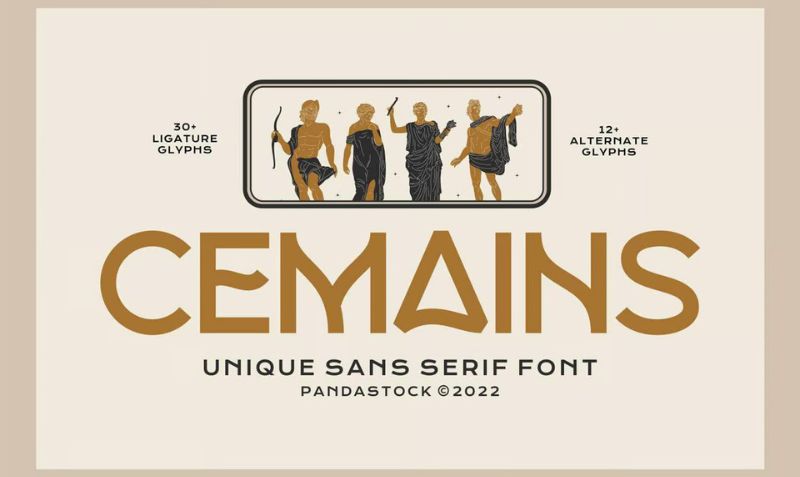
Font iCielBC Downtown
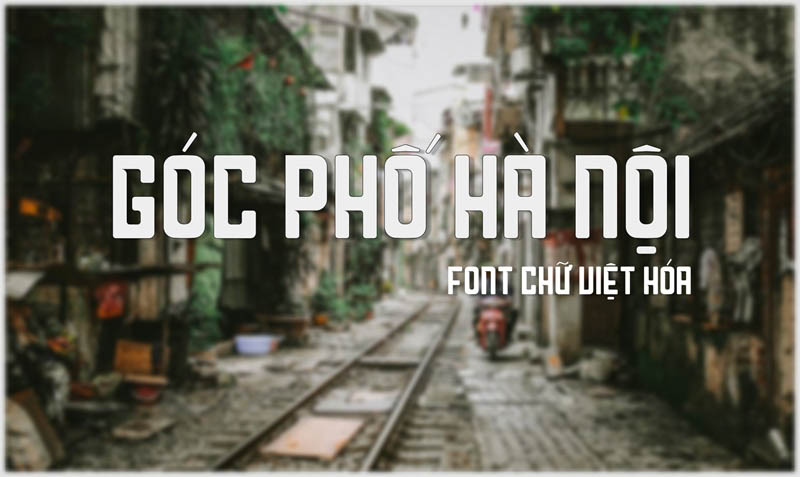
Được thiết kế bởi một bạn nữ ở Hà Nội, phông chữ iCielBC Downtown được lấy cảm hứng từ những tấm biển vẽ tay, những hình ảnh bình dị và màu sắc thời bao cấp. Tuy nhiên, chỉ nên sử dụng font này cho mục đích cá nhân, nếu dùng để thiết kế sẽ cần phải mua bản quyền.
Font SVN-Product Sans
Đây là phông chữ do Google Inc thiết kế với mục đích xây dựng thương hiệu riêng và dùng để thay thế logo Google vào tháng 9/2015. Bạn sẽ tìm thấy phông chữ này trong hầu hết các ứng dụng được cung cấp bởi Google.
Font Futura
Futura là một kiểu chữ sans serif được thiết kế bởi Paul Renner vào năm 1927, dựa trên các hình dạng hình học, đặc biệt là hình tròn, theo tinh thần của phong cách thiết kế Bauhaus thời bấy giờ. Cho đến ngày nay, đây vẫn là một trong những phông chữ được tìm kiếm nhiều nhất.
Font Bìa Sách Xưa
Phông chữ Bìa Sách Xưa được thiết kế bởi Tống Văn Điệp, ông đã lấy cảm hứng từ những bảng quảng cáo, trên bìa sách cũ của Việt Nam những năm 1980. Nét ngang dày cùng nét dọc mảnh mai của từng con chữ gợi lên cho người đọc cảm giác hoài cổ.
Font Bon Foyage
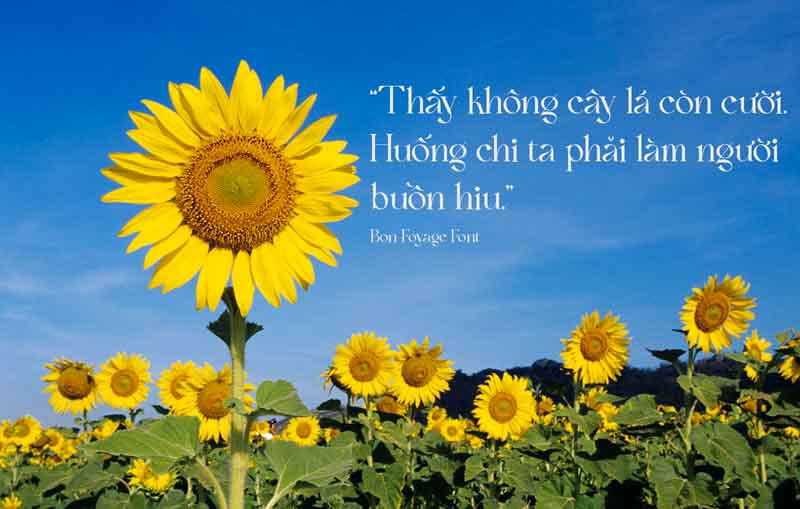
Phông chữ NVN Bon Foyage thuộc serifs thư pháp phong cách hiện đại, phù hợp với nhiều chủ đề thiết kế bao gồm thời trang, tạp chí, logo, thương hiệu, thiệp mời, trích dẫn, tiêu đề blog, áp phích, quảng cáo, bưu thiếp, sách và website.
Font chữ in hoa đẹp SVN-TheUntold Story
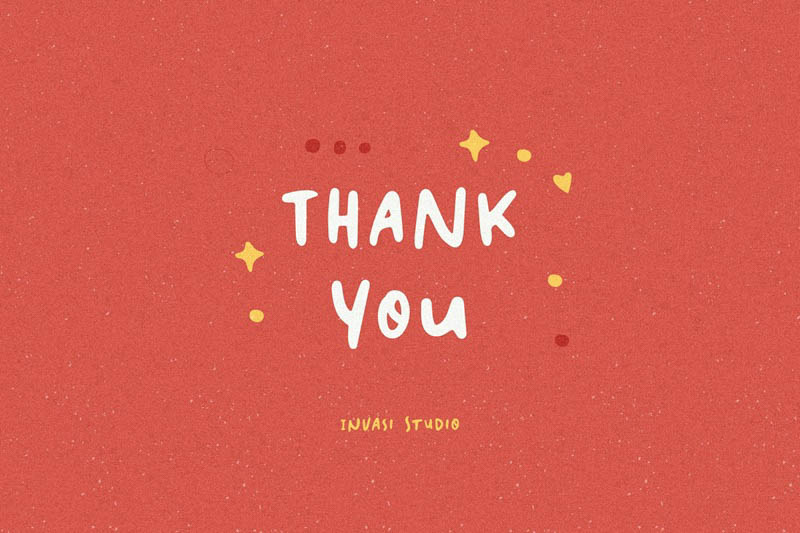
SVN-TheUntold Story là một phông chữ mang phong cách vui nhộn, đặc biệt phù hợp trong thiết kế các ấn phẩm tờ rơi, thiệp chúc mừng, bao bì sản phẩm, bìa sách, bìa album, thiết kế đồ họa, may mặc.
Font Hapna
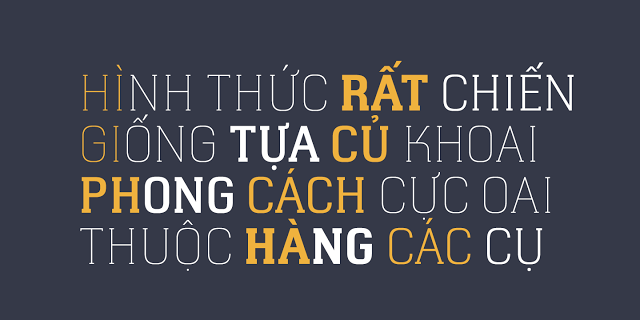
Hapna là phông chữ Slab Serif hình học có các đặc tính đặc biệt khác với các phông chữ Slab Serif trên thị trường, được lấy cảm hứng từ bóng chày và các ấn phẩm những năm 1950. Bộ font gồm 6 kiểu từ Light đến Black, đã được Việt hóa hoàn toàn.
Font Rukola
Font chữ in hoa đẹp Soup of Juice
Font Brandon
Brandon Text hiện là phông chữ bán chạy thứ ba mọi thời đại trên Myfonts. Phông chữ bao gồm 6 kiểu, được thiết kế bởi Hannes von Döhren vào năm 2012. Brandon Text phù hợp với các sản phẩm trên trang web, sách điện tử hoặc ứng dụng.
Font Kermel
Phông chữ Kermel có phong cách dí dỏm và vui nhộn cho các thiết kế biểu ngữ và áp phích sáng tạo.
Font chữ in hoa đẹp Roicamonta
Roicamonta là kiểu phông chữ viết tay được nhiều nhà thiết kế ưa thích và sử dụng trong các ấn phẩm nhẹ nhàng và lãng mạn như tiêu đề phim, video ca nhạc, áp phích truyện,…
Font Crocante
Font Latype
Bộ font Latype được thiết kế bởi Agung Syaifudin vào năm 2015 và hiện tại đã có rất nhiều phiên bản Việt hóa. Tuy nhiên, không được khuyến khích sử dụng cho mục đích thương mại.
Fabrizio
Fabrizio mang phong cách vui nhộn, cấu trúc độc đáo, với các nét dày và các đường cong nhẹ ở cuối các chữ cái. Ngoài bộ chữ Latin, Fabrizio còn hỗ trợ ligature của OpenType, hiện được bán trên YouWorkForThem và HypeForType với giá từ $20.